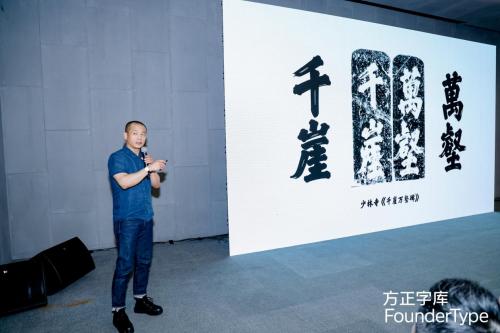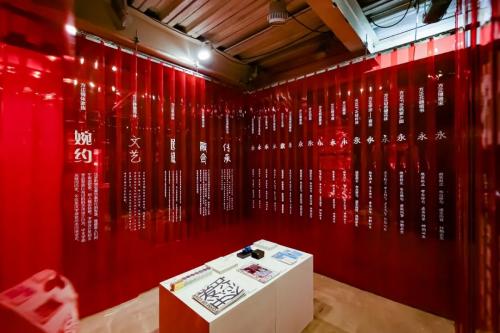
方正字库“文字光影”在深圳绽放 与行业专家共话字体设计未来
2023年9月22日,由国家语委中国文字字体设计与研究中心、北京北大方正电子有限公司(以下简称“方正电子”)、深圳市平面设计协会、深圳市甲古文创意设计有限公司联合主办的“文字光影”全国巡展深圳站开幕式暨“字创未来”设计论坛在深圳南山西丽万科云城设计公社圆满举办。“文字光影”设计大展为观众展示文字的优美与力量;《2023字体趋势报告》解读未来字体设计趋势;方正字库发布最新字体产品和技术;多位行业专家齐聚一堂,共话字体设计的未来。
“文字光影”全国巡展深圳站开幕式暨“字创未来”设计论坛发布会现场
活动当天,中共深圳市委宣传部二级巡视员、深圳创新创意设计发展办公室主任韩望喜,深圳市创意文化中心办公室负责人冯庆,深圳市平面设计协会学术委员王粤飞,深圳市平面设计协会主席张涛,深圳市平面设计协会顾问、昊格汉字高定设计总监张昊,深圳市平面设计协会顾问、华思品牌咨询创始人刘永清,深圳市甲古文创意设计有限公司创意中心总经理康伟杰,国家语委中国文字字体设计与研究中心副主任、方正电子副总裁兼方正字库总经理张建国,以及100多位设计师代表、企业代表、清华深圳国际研究生院、深圳大学和深圳职业技术大学等院校的师生代表线下参会,众多爱好字体的观众通过线上观看直播的方式,共同见证了此次大会的召开。
深圳市平面设计协会主席张涛致辞
方正电子副总裁兼方正字库总经理张建国致辞
定格光影感受文字力量
绚烂绽放的汉字,中华文化之魂,历经五千年的岁月洗礼,将华夏的风采一笔一画地书写。汉字作为文化的象征,见证着漫长的历史变迁,不同的书写形式和书体,则将我们带入一个个独特的文化画廊,呈现汉字的无尽变化。
7月15日至7月23日,“文字光影”全国巡展在北京751 D·PARK时尚设计广场轰轰烈烈举行。这场展览不同于以往的文字展览,以其独特的定格方式,让汉字演变历程中的千姿百态尽收眼底。展览分为四个精彩版块:「千古风流之美」展示了方正字库倾力打造的“中华精品字库工程”中40款精品字体,通过科技的力量,让观众近距离感受历代名家的书法神韵;「探索无限可能」以多样化、创意化的字体作品让观众享受了丰富多彩的视觉盛宴;「聆听品牌声音」中许多品牌通过定制字体,将自己的品牌故事传递给大众,展现核心价值和特点;「字体未来之光」展出了历届方正奖设计大赛的获奖作品,让观众一览未来的文字设计。
方正字库“文字光影”全国巡展北京站展览现场
为了让更多的观众能够沉浸式感受文字之美,欣赏更为丰富多元的艺术设计,“文字光影”全国巡展的第二站来到了深圳。在发布会现场,方正字库设计总监汪文介绍了展览内容,中共深圳市委宣传部二级巡视员、深圳创新创意设计发展办公室主任韩望喜,深圳市创意文化中心办公室负责人冯庆,深圳市平面设计协会学术委员王粤飞,深圳市平面设计协会主席张涛,深圳市甲古文创意设计有限公司创意中心总经理康伟杰,方正电子副总裁兼方正字库总经理张建国一起上台启动,“文字光影”全国巡展深圳站正式开幕。
方正字库“文字光影”全国巡展深圳站展览现场
方正字库“文字光影”全国巡展深圳站开幕启动仪式
方正字库发布解读《2023字体趋势报告》
在迅速发展的数字化时代,字体已经成为品牌形象、用户体验、视觉传达的重要载体,字体的设计、选择与应用具有举足轻重的作用。作为中文字体领域的领导者,方正字库基于三十多年的探索与实践,总结出全新的《2023字体趋势报告》。发布会现场,深圳市平面设计协会会员、方正字库设计总监汪文介绍了三大字体趋势:传承经典书法、数字化手写字体和古籍复刻字体。方正字库高级字体设计师梁标解读了字体创意、汉字文化圈和字体全球化三项趋势。方正字库客户服务部总经理高雪分享了品牌定制、可变字体、新标准汉字和AI技术四大趋势。《2023字体趋势报告》为字体设计从业者和平面设计工作者提供了启示和参考,激发创作者不断探索以展现汉字的力量和美感。
方正字库设计总监汪文解读字体趋势
方正字库高级字体设计师梁标解读字体趋势
方正字库客户服务部总经理高雪解读字体趋势
在《2023字体趋势报告》中,方正字库梳理当前字体应用市场流行的字体风格,探讨各趋势背后的审美理念与设计原则,并总结新兴技术对字体设计的影响,为字体设计从业者、字体创作者、平面设计工作者、社会大众提供启发和参考,激发设计创作者不断探索,让更多人能在日常生活中随时随地感受到汉字的力量和美好。
方正字库携手少林寺发布少林功夫体
在设计全球化的时代背景下,为推动中华文化在全球范围内传播、交流和发展,方正字库与全球知名文化机构少林寺联合,倾力打造了融合少林功夫与汉字文化的字体产品——方正少林功夫体。这款字体不仅融入了中国特色传统文化的元素和美学,更被打造为一款包含全球多语言文种的超大字库,具有独特的艺术魅力、文化内涵和实用价值。
方正少林功夫体
活动现场,方正字库副总经理黄学钧向大家隆重介绍了方正少林功夫体,针对这款重磅字体产品的创作背景、灵感来源、设计细节进行了全方位地深度解析。作为少林寺独特的文化符号,少林功夫体将少林功夫文化与汉字文化相结合,包括日文、韩文等多国外文,助力中华武术文化对外交流传播,走向世界。
方正字库副总经理黄学钧解读少林功夫体
嘉宾共话字体行业未来
在本次设计大会上,方正字库邀请了两位设计专家进行“文字设计与品牌定制”的主题分享。深圳市平面设计协会顾问、昊格汉字高定设计总监张昊以《字游天地:汉字高定》为主题,分享了字体设计的相关内容。张昊提出“品牌文字设计,既是对品牌内涵的梳理和呈现,亦是对她的焕新和再造,既是可传播形象的品牌载体,也是可传递资讯的文本内容,既是回望过去,更是面向未来”。
昊格汉字高定设计总监张昊发表演讲
随着市场竞争的加剧,众多企业寻求新的视觉表达方式,打造更具品牌特性的专属形象,字体定制的需求应运而生。深圳市平面设计协会顾问、华思品牌咨询创始人刘永清以《品牌字体定制》为主题分享了独到见解。“一形二构三重心,气韵生动是核心”,刘永清为现场及线上观众分享了他对字体设计的归纳总结,并分享了海底捞、祁门红集团等诸多品牌定制案例。
华思品牌咨询创始人刘永清发表演讲
“字创未来”设计论坛精彩开讲
大会当天,举行了字体设计及应用趋势圆桌论坛,吸引了众多业内专家学者和特邀演讲嘉宾的参与。论坛的嘉宾包括深圳市平面设计协会学术委员王粤飞,深圳市平面设计协会主席张涛,深圳市平面设计协会顾问、昊格汉字高定设计总监张昊,深圳市平面设计协会顾问、华思品牌咨询创始人刘永清,方正字库设计总监汪文。嘉宾们围绕字体设计的新理念和行业趋势展开了热烈讨论,为字体设计和爱好者们带来了许多启发。
方正字库“字创未来”设计论坛
在数字化时代,字体设计行业面临着机遇和挑战。通过继续探索和创新,中文字体设计行业将会迎来更美好的未来。从探索出发,感受精美字体蕴含的无限魅力,感受中文字体未来的无限可能。